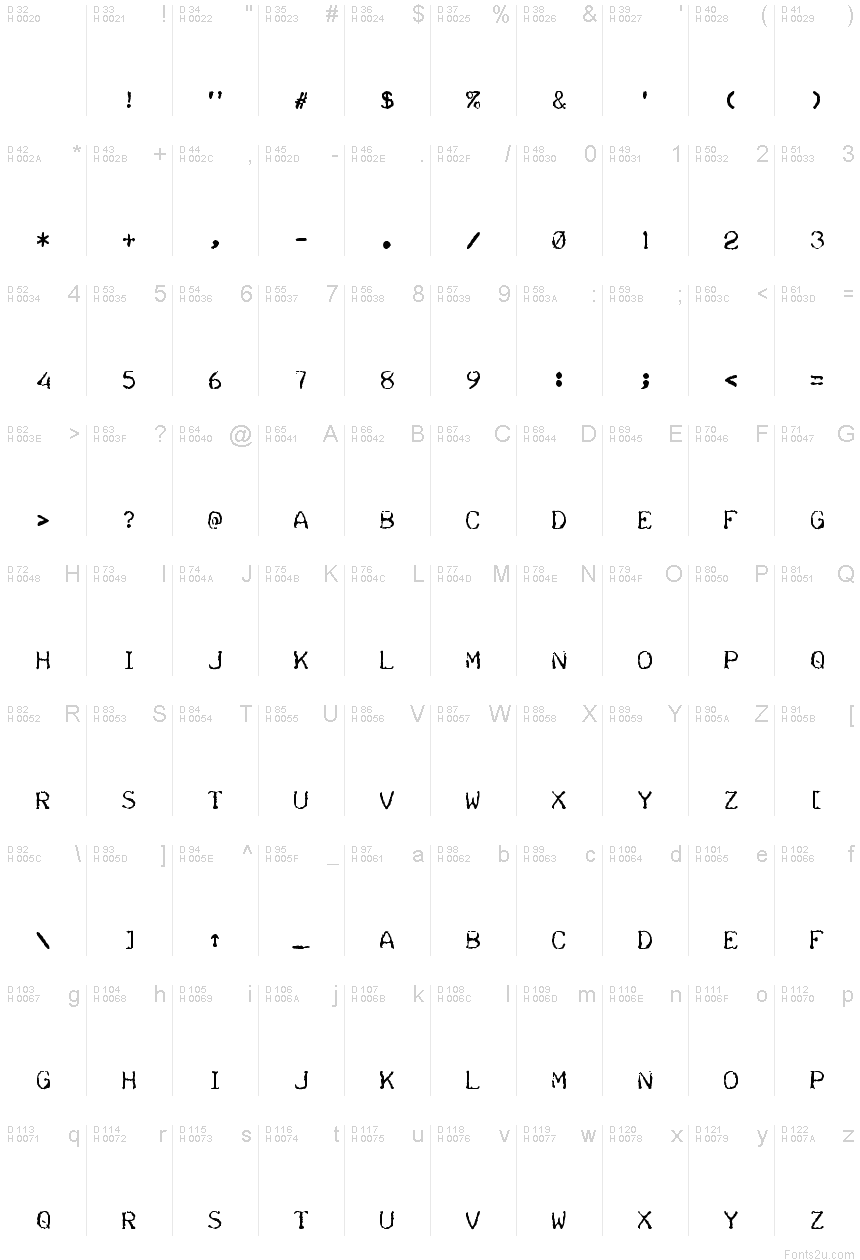
Teleprinter, autorstwa Marka Zanziga, to darmowy, erodowany krój typu display, który oddaje surowy charakter starych odbitek atramentowych i niedoskonałego druku maszynowego. Litery sprawiają wrażenie wytartych na krawędziach, z miękkimi śladami odbić, zlanymi łączeniami i lekko nieregularnymi konturami, co nadaje wielkim literom surowy, znoszony rytm.
Krój ten idealnie pasuje do plakatów, okładek zinów, kart tytułowych, opakowań i ulotek, wszędzie tam, gdzie zależy Ci na literach, które wydają się „dotknięte” ręką, a nie dopracowane. Jako darmowy font, świetnie sprawdzi się też w krótkich nagłówkach, logotypach stylizowanych na pieczątki oraz w otwarciach rozdziałów – nadgryzione kształty wnoszą zużytą, mechaniczną teksturę nawet w krótkich tekstach.